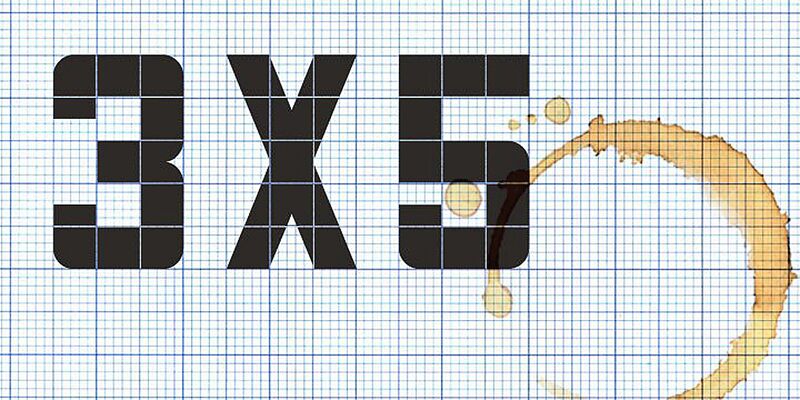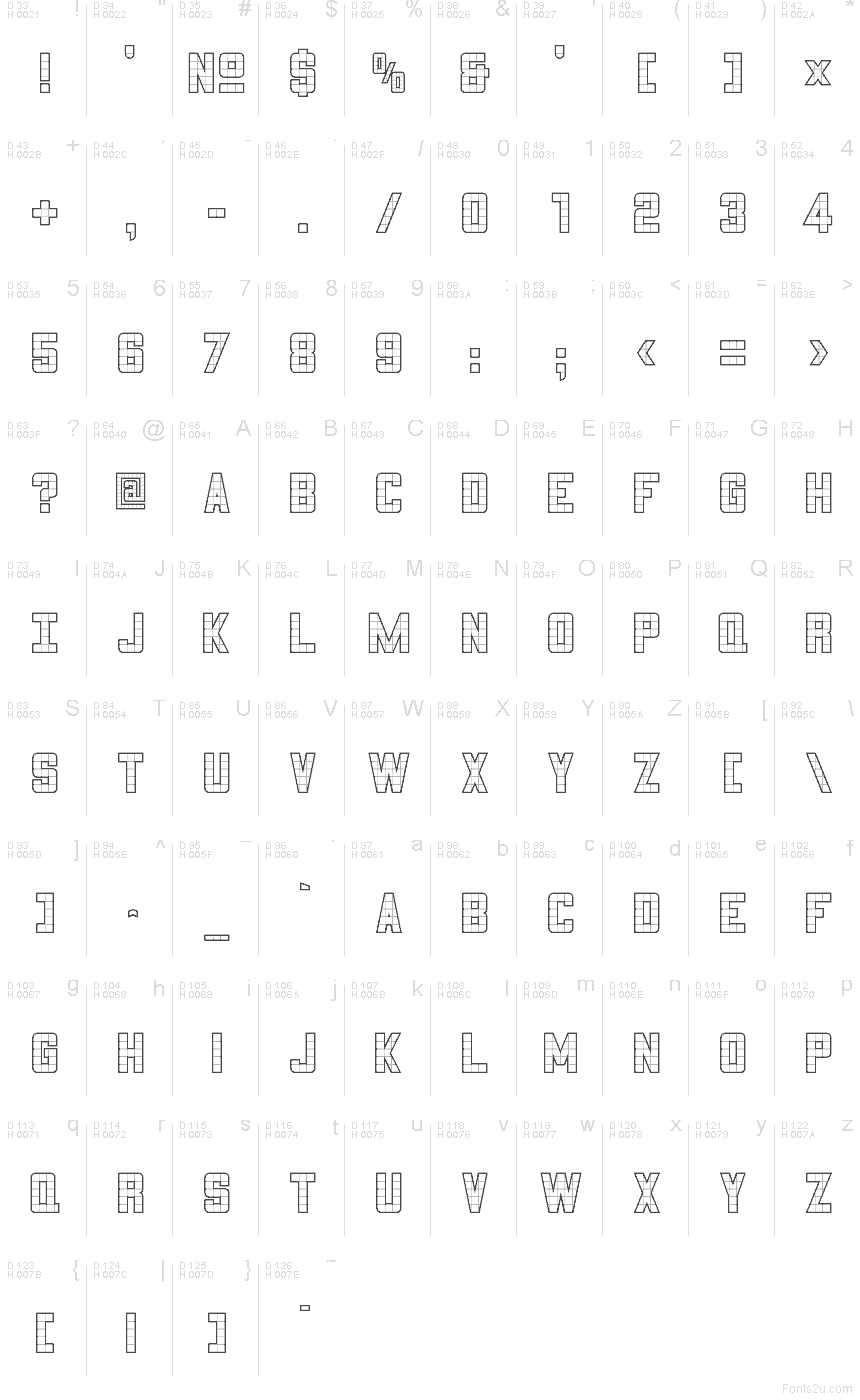
35 a 35 Outline jsou verzálková (all-caps) display písma založená na jednoduché, ale osobité logice mřížky: většina znaků je zkonstruována v rámci rastru tři čtverce na šířku a pět na výšku. Jejich původ leží ve čtvercových, ručně kreslených písmenech, která se dříve používala na výtvarných složkách na bývalé Joseph Eastham High School v Salfordu, kde byla písmena pečlivě rýsována na 1cm čtverečkovaný papír. V těchto digitálních interpretacích není tato základní struktura skryta, ale naopak oslavována; čtvercové moduly a vnitřní členění zůstávají viditelné a tvoří určující dekorativní prvek každého znaku.
Výsledkem je dvojice písem, která působí zároveň účelně i výrazně. Z jejich konstrukce vyzařuje tichá poctivost připomínající éru, kdy se písmo měřilo, navrhovalo a tvořilo ručně. Pevná mřížka zároveň dodává slovům jemný rytmus a konzistenci, což textu propůjčuje ucelenou, téměř architektonickou kvalitu.
35 má solidní, sebevědomou přítomnost, zatímco 35 Outline nabízí lehčí a otevřenější protějšek. Obě písma evokují modulární nápisy, které se nacházely ve veřejných prostorách poloviny 20. století, jako jsou nádraží, bazény, školní chodby a úřední budovy, kde byla odolnost a čitelnost prvořadá. Toto spojení jim dodává jemný nádech nostalgie, aniž by je vázalo ke konkrétnímu dobovému stylu.
Vysoce čitelná a vizuálně působivá písma jsou velmi vhodná pro sportovní branding, tvorbu plakátů, značení a merchandising, kde je klíčová výraznost a jasnost. Verze 4.0 (2026) přináší vylepšené obrysy a lepší konzistenci.
Based on the squared lettering used for art folders at the former Joseph Eastham High School in Salford, most letters being three squares wide and five squares tall.